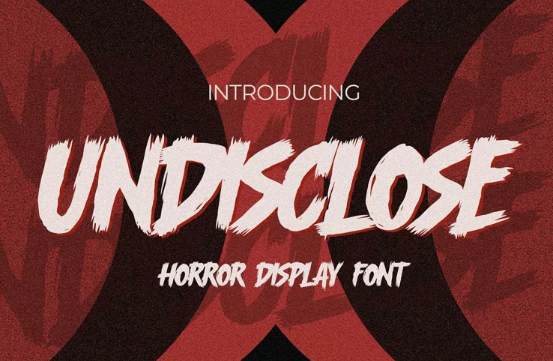
[Fontbundles] Undisclose Font (2022)
Привет всем, представляем наш новый продукт Шрифт UNDISCLOSE это Horror Display Font.This is a Textured Natural Style and Strong style with a Cool style and dramatic movement.
Этот шрифт UNDISCLOSE отлично подходит для ваших следующих творческих проектов, таких как логотипы, печатные цитаты, приглашения, открытки, упаковка продуктов, заголовки, логотип, бланк письма, плакат, дизайн Этот шрифт отлично подходит для ваших творческих проектов, таких как водяной знак на фотографии, и идеально подходит для логотипов и брендинга, приглашения, реклама, дизайн продуктов, канцелярские принадлежности, свадебные дизайны, этикетки, упаковка продуктов, специальные мероприятия или все, что нужно рукописный вкус.
Привет всем, представляем наш новый продукт Шрифт UNDISCLOSE это Horror Display Font.This is a Textured Natural Style and Strong style with a Cool style and dramatic movement.
Этот шрифт UNDISCLOSE отлично подходит для ваших следующих творческих проектов, таких как логотипы, печатные цитаты, приглашения, открытки, упаковка продуктов, заголовки, логотип, бланк письма, плакат, дизайн Этот шрифт отлично подходит для ваших творческих проектов, таких как водяной знак на фотографии, и идеально подходит для логотипов и брендинга, приглашения, реклама, дизайн продуктов, канцелярские принадлежности, свадебные дизайны, этикетки, упаковка продуктов, специальные мероприятия или все, что нужно рукописный вкус.